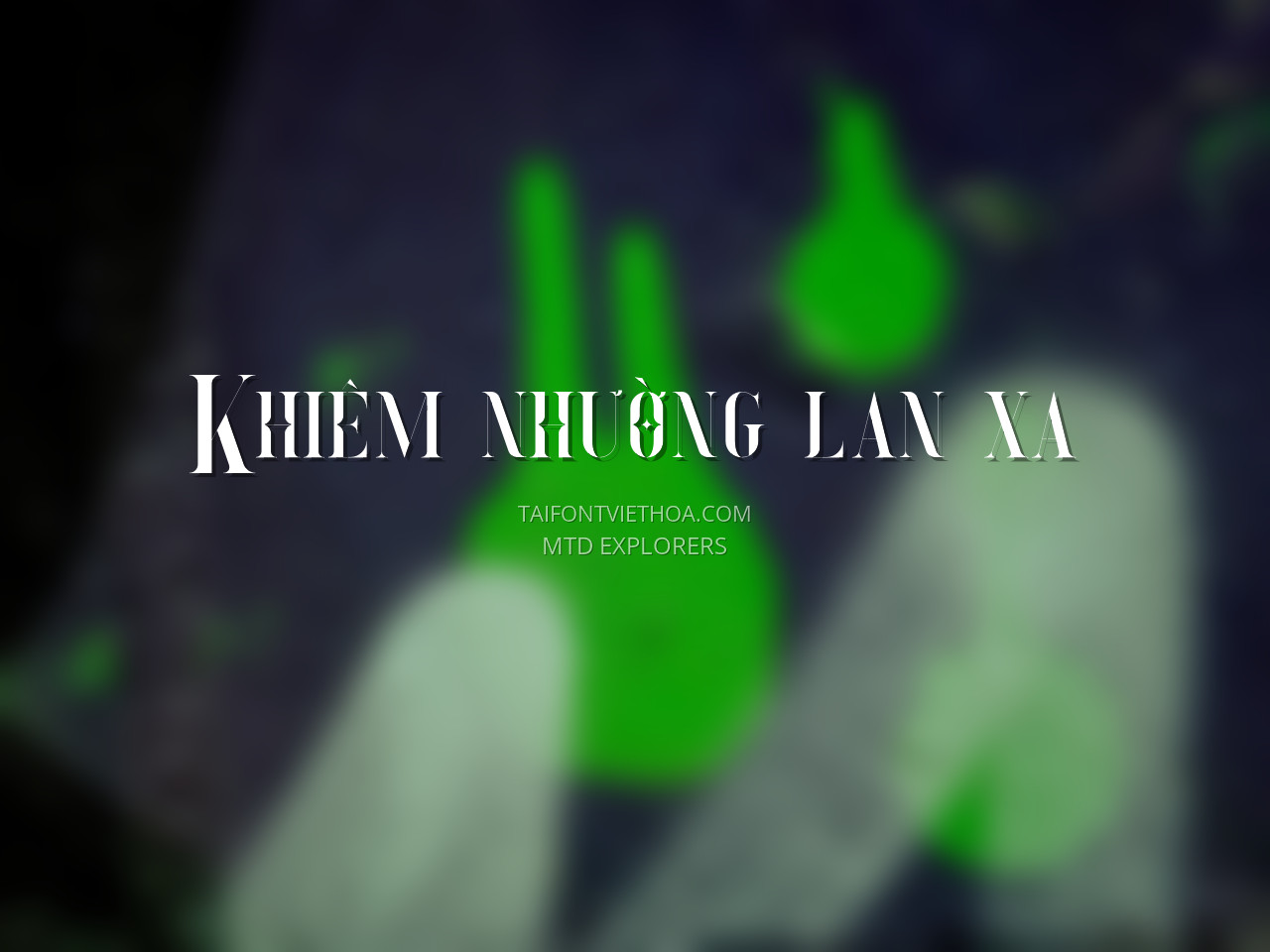
Font việt hóa MTD Explorers
Tác giả Font: Vpcreativeshop
Giới thiệu về font Explorers
Explorers là một font chữ hiển thị (display) đậm chất phiêu lưu, được thiết kế bởi Motokiwo Type (MTD) với cảm hứng từ các hành trình khám phá thiên nhiên và vùng đất mới. Font mang đến cảm giác năng động, hoang dã và đầy bản sắc nam tính, phù hợp với các dự án thiết kế hướng tới phong cách phiêu lưu, mạnh mẽ hoặc cổ điển. Phiên bản Việt hóa được thực hiện bởi chính MTD, hỗ trợ đầy đủ tiếng Việt và hơn 70 ngôn ngữ khác, rất lý tưởng cho các thiết kế đa ngôn ngữ nhưng vẫn muốn giữ phong cách đậm cá tính.
Đặc điểm thiết kế và ứng dụng của font Explorers
Explorers sở hữu các ký tự đậm, cứng cáp với các nét gãy và bo góc mạnh mẽ. Font có phần hơi góc cạnh nhưng vẫn giữ được sự cân đối trong từng chữ cái, tạo nên cảm giác chắc chắn và dễ đọc ở mọi kích thước. Với tone thiết kế cổ điển hiện đại pha trộn, Explorers rất thích hợp dùng cho logo thương hiệu outdoor, nhãn bao bì thủ công, hoặc thiết kế poster sự kiện ngoài trời.
Ứng dụng lý tưởng: logo đồ lưu niệm, nhãn hiệu cà phê rang xay, sản phẩm da thủ công, tiêu đề blog du lịch, sticker dã ngoại, bản đồ minh họa, bìa sách phiêu lưu hoặc đồ họa cổ điển. Ngành nghề phù hợp: du lịch, sản phẩm thủ công, thời trang retro, thực phẩm organic, thiết kế branding outdoor và các dự án mang hơi hướng khám phá, bản địa hóa.